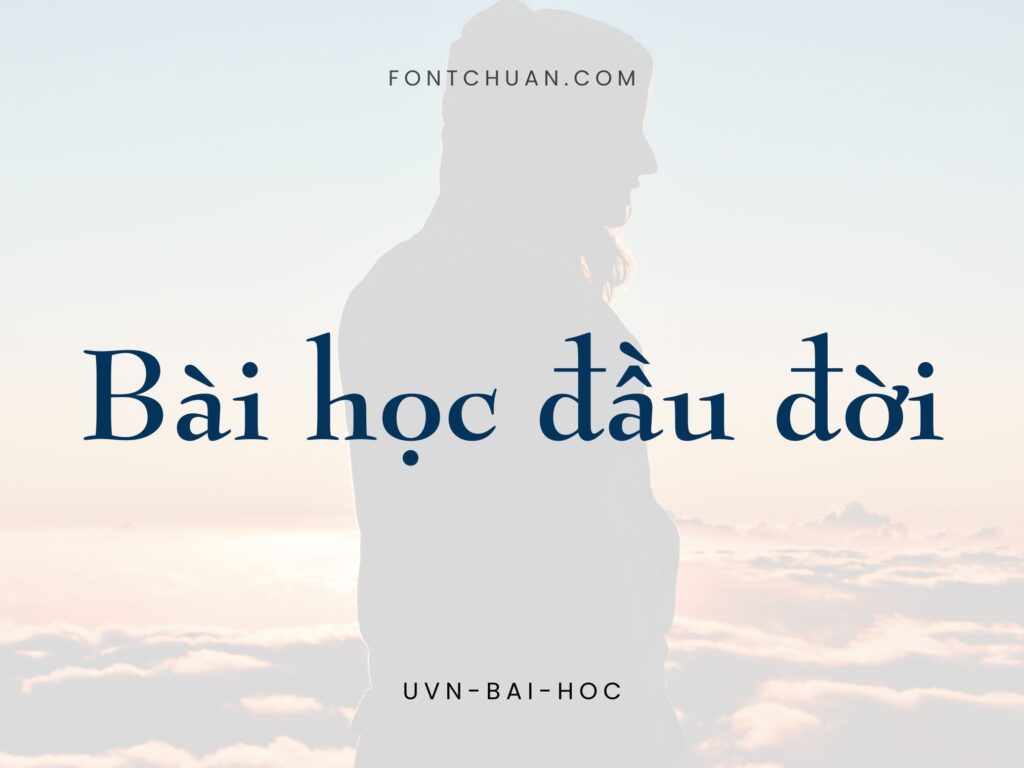
Font UVN Bai Hoc Việt Hóa
UVN Bài Học là một kiểu chữ serif được thiết kế với các đường nét thanh mảnh và tinh tế, mang đến vẻ đẹp cổ điển và trang nhã. Font này chỉ được sưu tầm và đăng bởi thành viên của Font Chuẩn.
UVN Bài Học có cấu trúc chữ với các nét mảnh mai và chân chữ rõ ràng, tạo nên sự thanh lịch và dễ đọc. Font này phù hợp cho các ứng dụng như thiết kế sách giáo khoa, tài liệu học tập, giáo trình và các ấn phẩm in ấn yêu cầu sự trang trọng và dễ tiếp cận. Các ngành nghề như giáo dục, quảng cáo, công nghệ và bất động sản có thể tận dụng UVN Bài Học để tạo điểm nhấn chuyên nghiệp trong thiết kế.